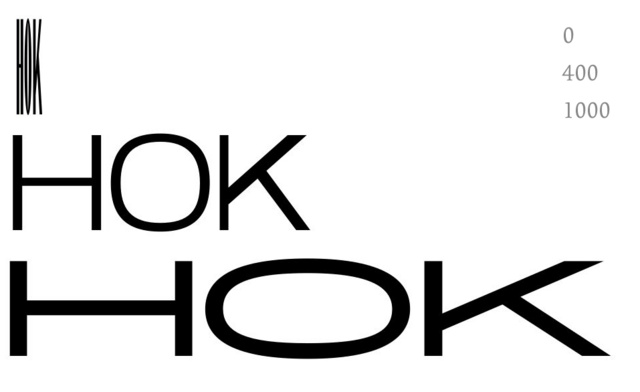
Multiple-Master-Instanzen
Ich arbeite zur Zeit an einer Schrift mit hilfe der Multiple Master Technologie und Fonlab 5.
Nach einiger Zeit Herumprobiererei und dem Wälzen von Manuals komme ich nun echt nicht weiter.
Deshalb hoffe ich mir kann jemand aus dem Forum helfen.
1.
Ich habe eine Achse Condensed und Extended. Einige Buchstaben (meistens mit Diagonalen) der Mittelinstanz
bekommen auf Teufel komm raus nicht die gleiche optische Strichstärke der Übrigen (z.B "n"). Sie erscheinen meist zu Fett, obwohl in den Condensed und Extended Instanzen alles angepasst wurde und optisch passt.
Bild als Illustration, unmerged Glyphs)
die Fragen:
Wieso interpoliert das Programm meine Diagonalen so seltsam? und gibt es einen Trick um den Fehler auszutricksen
(Beim "M" kann ich die Schultern abflachen und anspitzen, bei den Guillemots kann ich etwas proportional skalieren.
Aber beim "K" [klassizistisch] sind mir die Hände gebunden)
Kann ich einen Master überhaupt verwenden ohne das ich die Zwischeninstanzen nachträglich bearbeiten muss?
2.
Kann ich mir einen Wert der Master Achse (z.B. 409 als Mitte) irgendwie als Preview in das GlyphTable einstellen.
Ich meine damit die Übersicht wo alle Glyphen im Setzkasten stehen. Jetzt scheint er mir Irgendeine Instanz vorzusetzen, die weder 0, 500 noch 1000 ist. Mich irritiert, welchen Wert er da als Standart benutzt.
3.
Und eine Frage zuletzt. Kann ich irgendeinen bearbeitbaren Mittelwert in der Masterachse festlegen, sodass ich nicht nur
0 und 1000, sonder z.B. auch 409 bearbeiten kann. Sozusagen als Zwischenreferenz der Interpolation?
O
2)
wen du unter file > font info > multiple master settings den standartwert auf "409" setzt, siehst du in der glyphenübersicht immer diesen mittelwert beider instanzen.
in der ansicht einer einzelnen glyphe kannst du über window > panels > axis den entsprechenden wert für weight eingeben, der dann über den preview-mode (apfel+shit+p) sichtbar wird -> so hast du eine ungefähre live-vorschau was mit der "409"-instanz passiert, wenn du einen der beiden master änderst.
sehr geil ist auch http://www.yanone.de/typedesign/autopsy/ mit diesem programm kannst du – zumindest zum späteren überprüfen – ein pdf erstellen, indem nicht nur die 2 master, sondern auch beliebig viele zwischen instanzen visuell aufgelistet sind – und das ohne jede Instanz einzeln zu generieren, zu exportieren und in InDesign zu setzen …
3) nicht ganz das was du suchst aber etvl. hilfreich: mit der glyphs.app oder im superpolator könntest du dir die mittelinstanz abgreifen, als einzelnen font optimieren und schlussendlich wieder in auf eine der master-achsen setzen.
so hättest du z.b auf der weight-achse 3 instanzen: einen idealen light-schnitt, einen idealen bold-schnitt und dazwischen einen idealen regular-schnitt der dann nicht nur produkt der interpolation ist, sondern den weiten weg zwischen light und bold in der mitte nochmal korrigiert.
die idee der kontrollierten interpolation kannst du hier http://itunes.apple.com/de/podcast/robothon-2009/id309635402# in einem podcast über den superpolator nachsehen.
und auch zu yanones autopsy gibt es eine kurze einführung: http://itunes.apple.com/de/podcast/robothon-2009/id309635402#
ich hoffe das bild hängt jetzt an.
bin sehr glücklich über den fontinfo-trick...hab ich wohl übersehen.
den part mit dem superpolator werde ich mal versuchen.
yanone kenn ich, sehr geil, leider nur ein uninteraktives pdf... :)
Wow, das ist wirklich eine extreme Interpolation! Kein Wunder, dass da nie ein vernünftiger Schnitt in der Mitte entsteht. Entweder solltest du den bereits angesprochenen Weg über ein externes Programm gehen, bei dem du die mittlere Version selbst als Master bearbeitest, oder dich von den bisherigen Extremen lösen. Die ultra-condensed könnte man auch einfach als eigenen Schnitt zeichnen. Sie muss nicht die Grundlage für die Interpolation des Regular-Schnittes sein.
Dritte Möglichkeit: Gehe auf 2 Achsen, also 4 Master. Du mischst im Moment Weight und Width – was die Sache nicht einfacher macht.
ja...
die extreme ist das konzept, und die mitte fast überraschung.
gefeilt werden muss da so oder so, sonst kommt da keine familienähnlichkeit.
die mischung von width und weight ist ja aufgrund der architektur bedingt,
aber es kann schon sein, das das etwas extrem geworden ist, werde da
die schnitte nochmal angleichen.
bis auf die diagonalen klappt auch alles, aber wenn du meinst das liegt an der
reichweite, dann muss ich da wirklich nochmal überlegen.
variante 3 klingt interessant...
danke
was mir gerade zu 3) zwischeninstanzen direkt editieren einfällt, weil ich selber dran sitze:
in der glyphsapp hast du ein preview fenster, um die schrift parallel auch in kleinen punktgrößen zu sehen.
wenn man dann zwei master und eine zwischeninstanz definiert hat und das preview fenster sehr groß zieht, dann kann man zumindest die zwischeninstanz sehr gut beobachten, während man editierend zwischen den mastern wechselt — also fast ein direktes editieren der interpolierten intanzen.